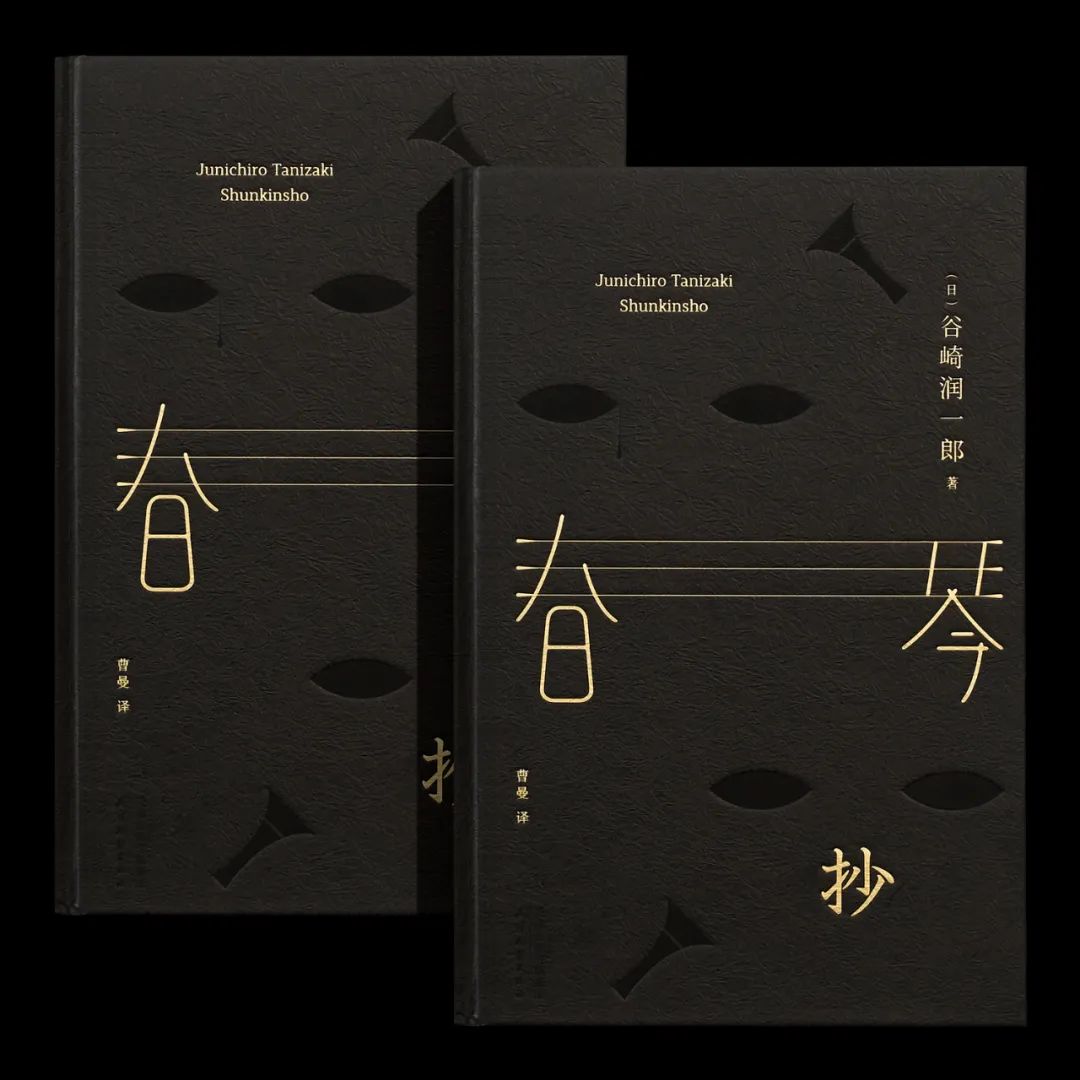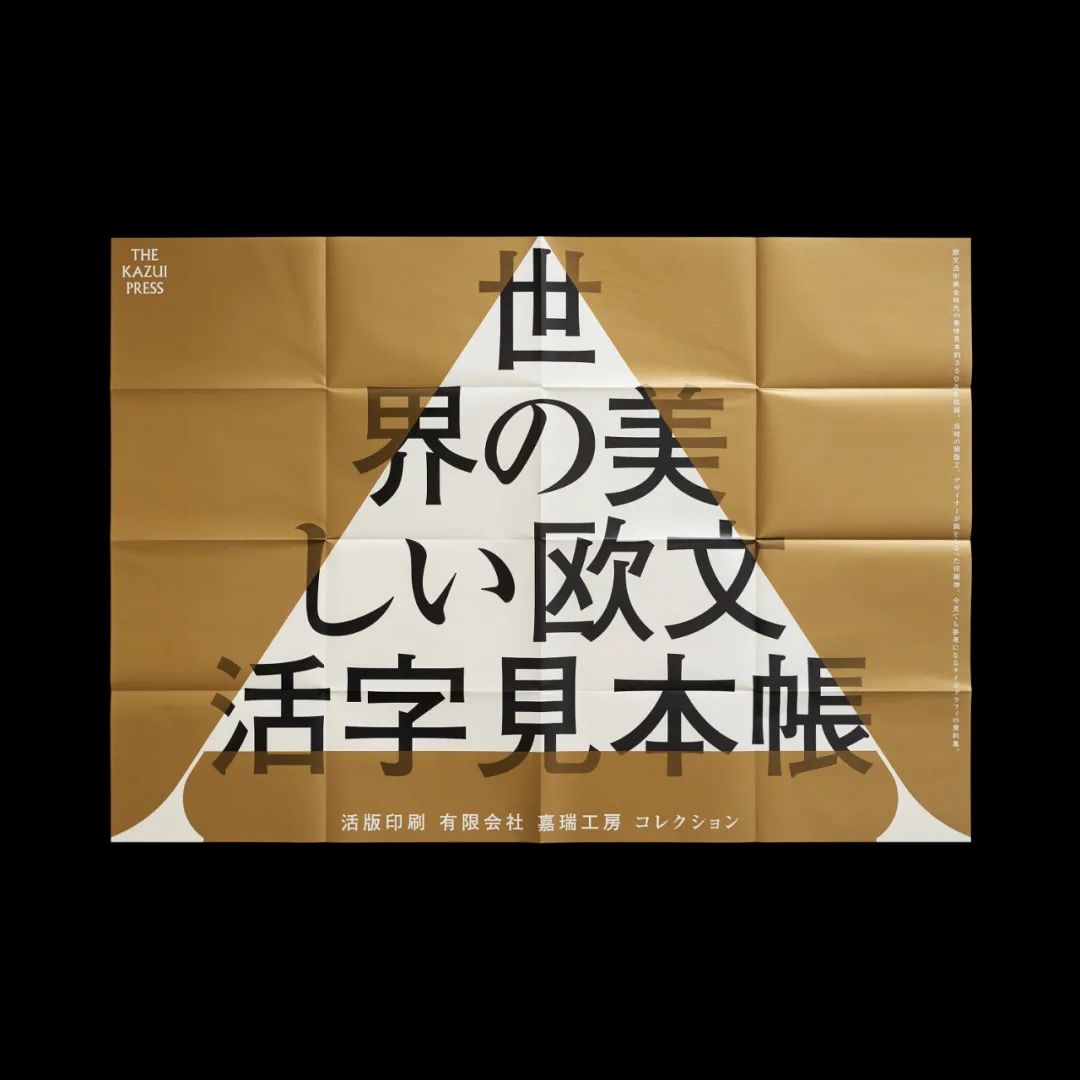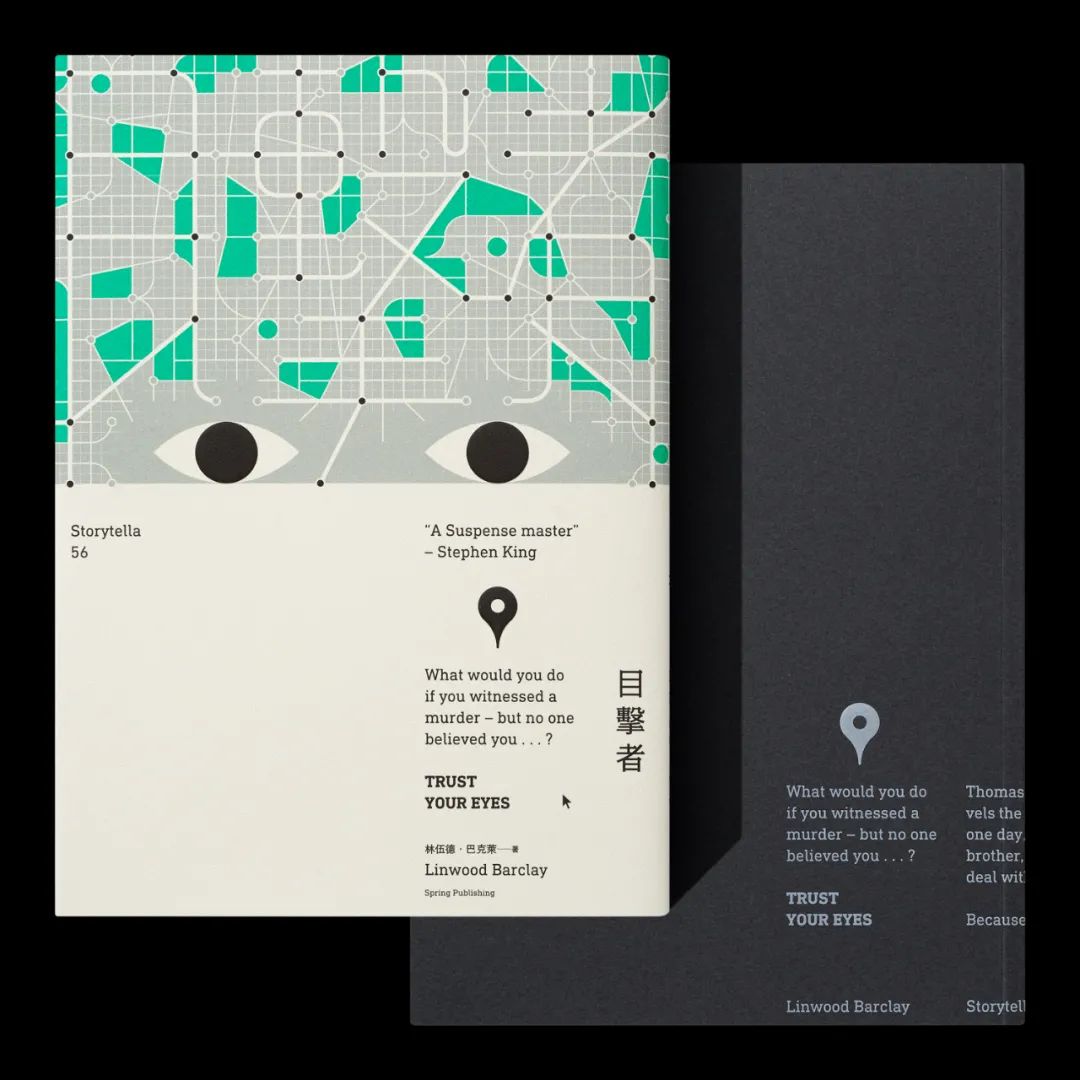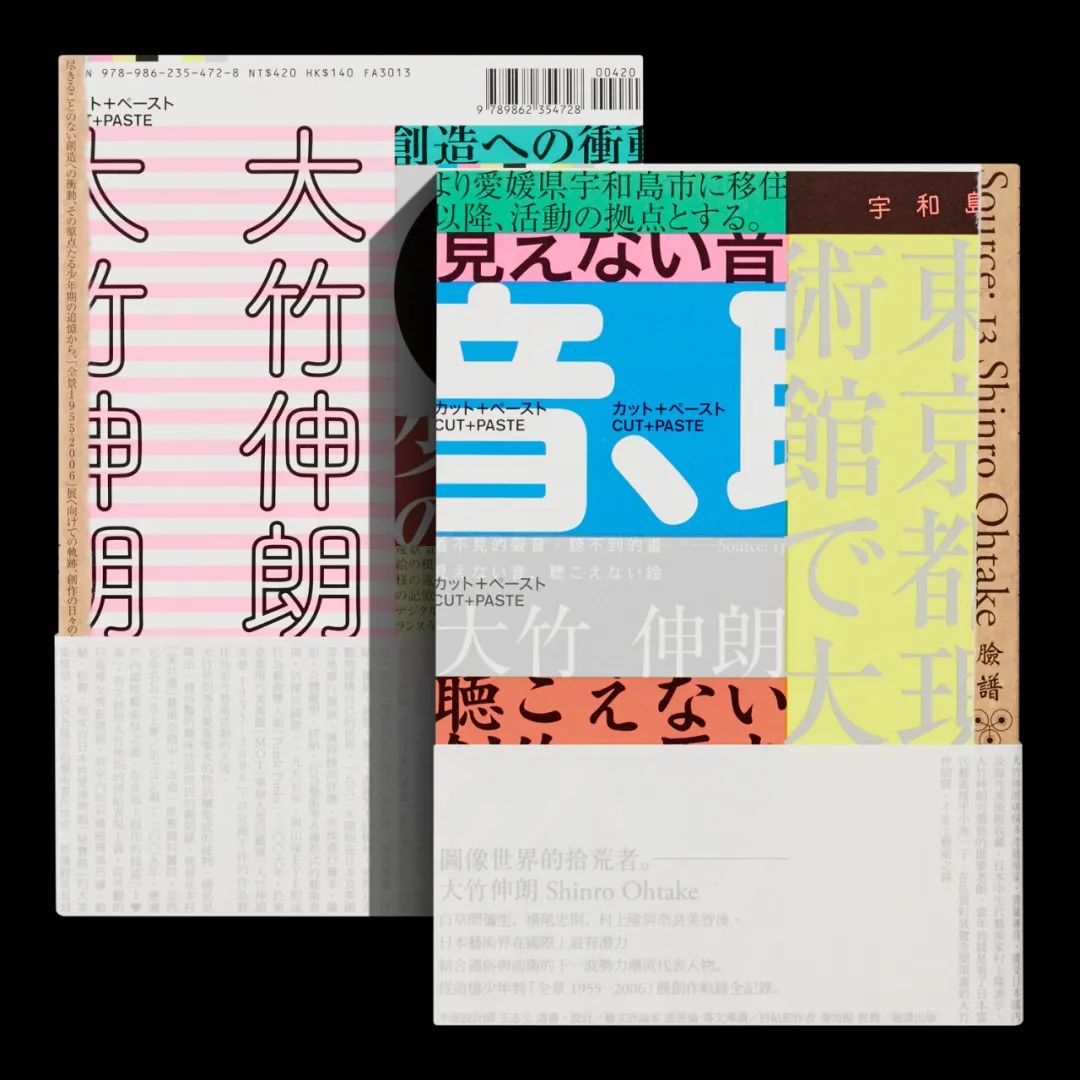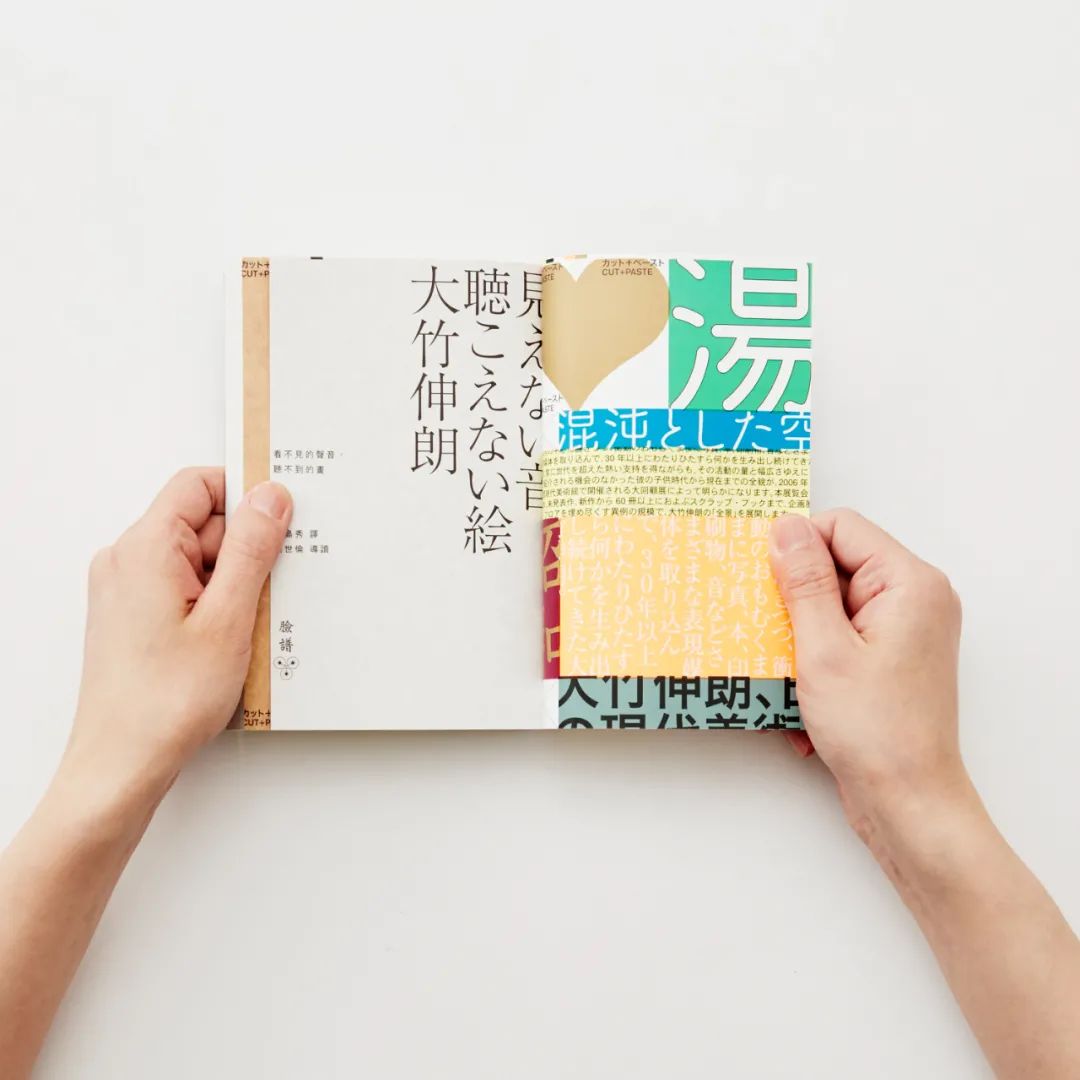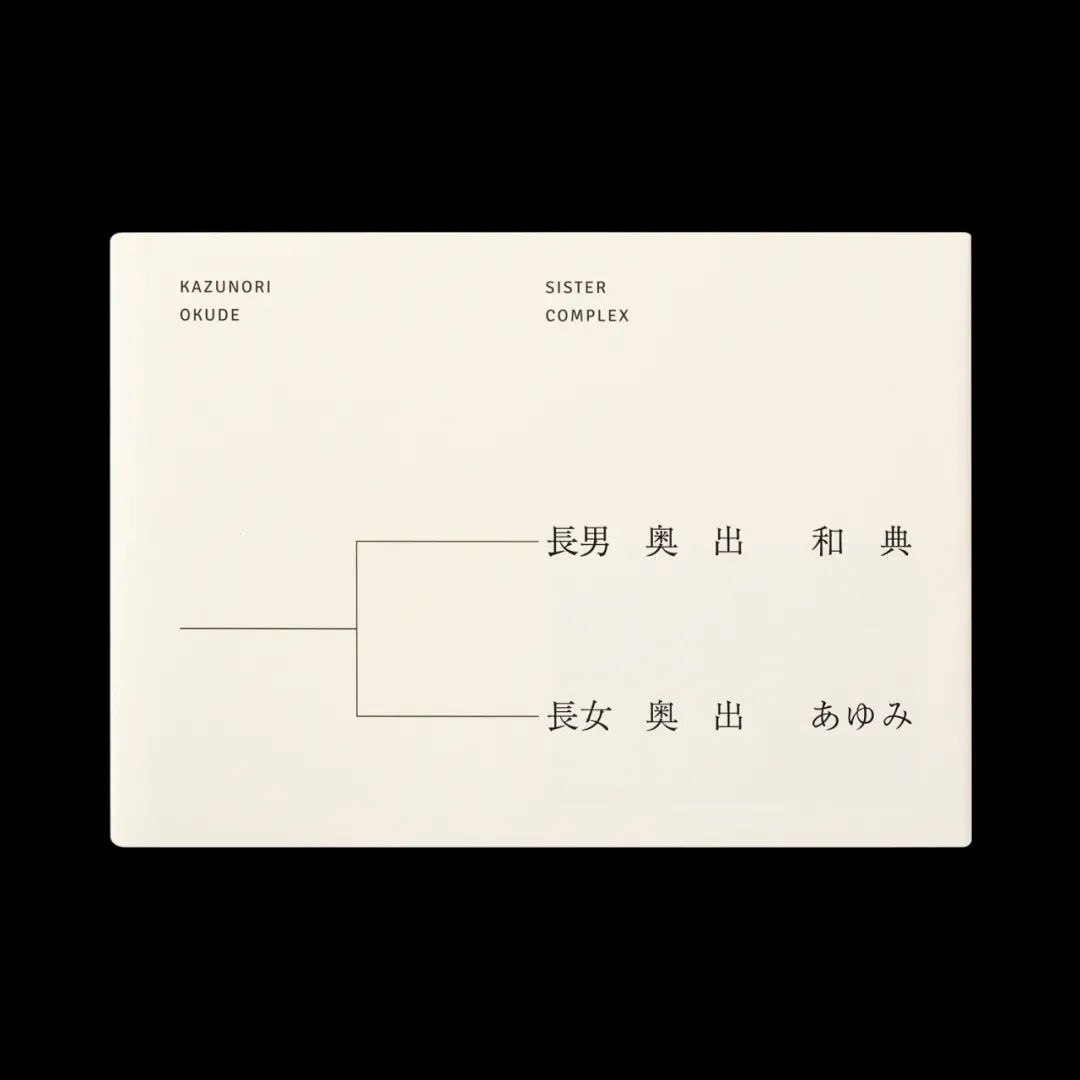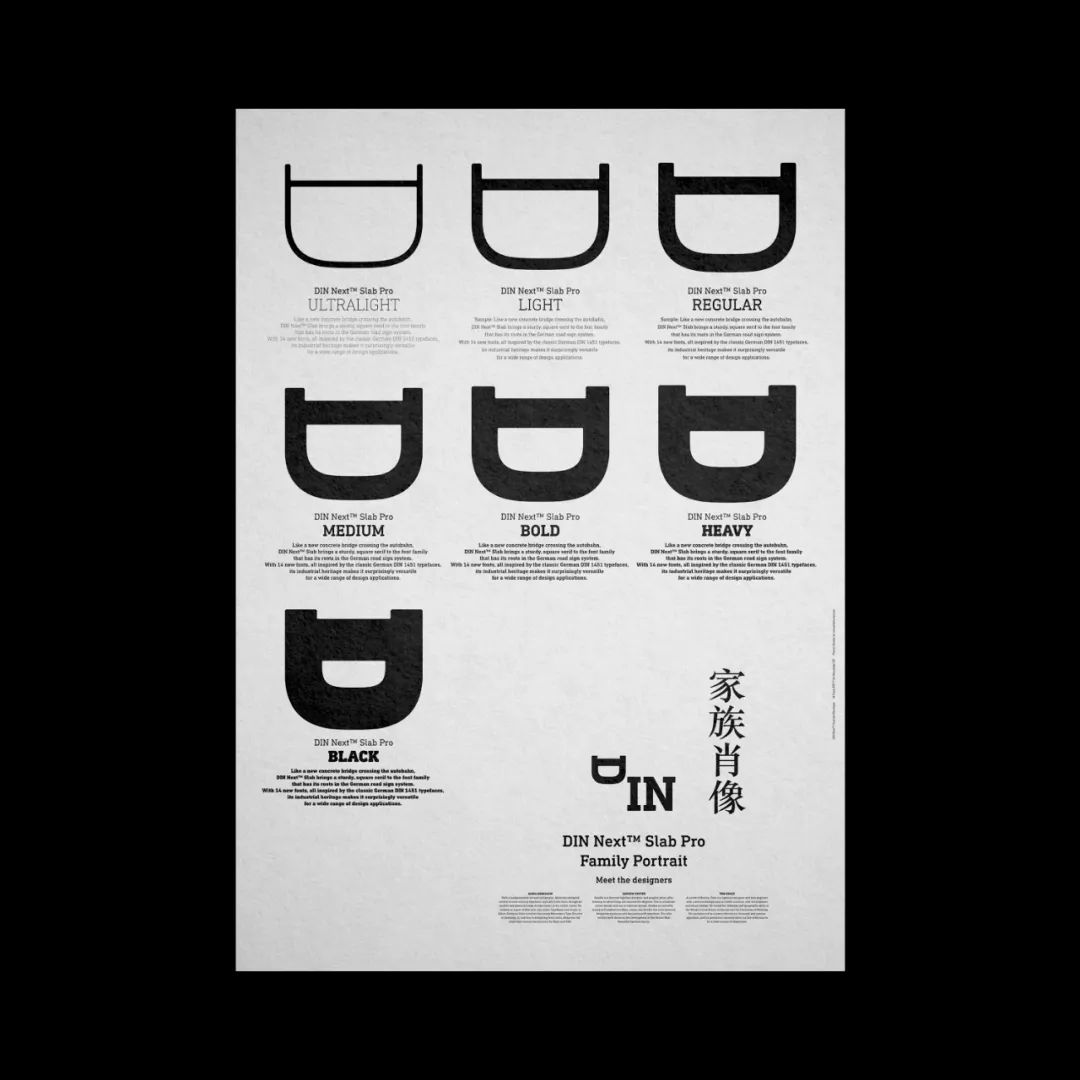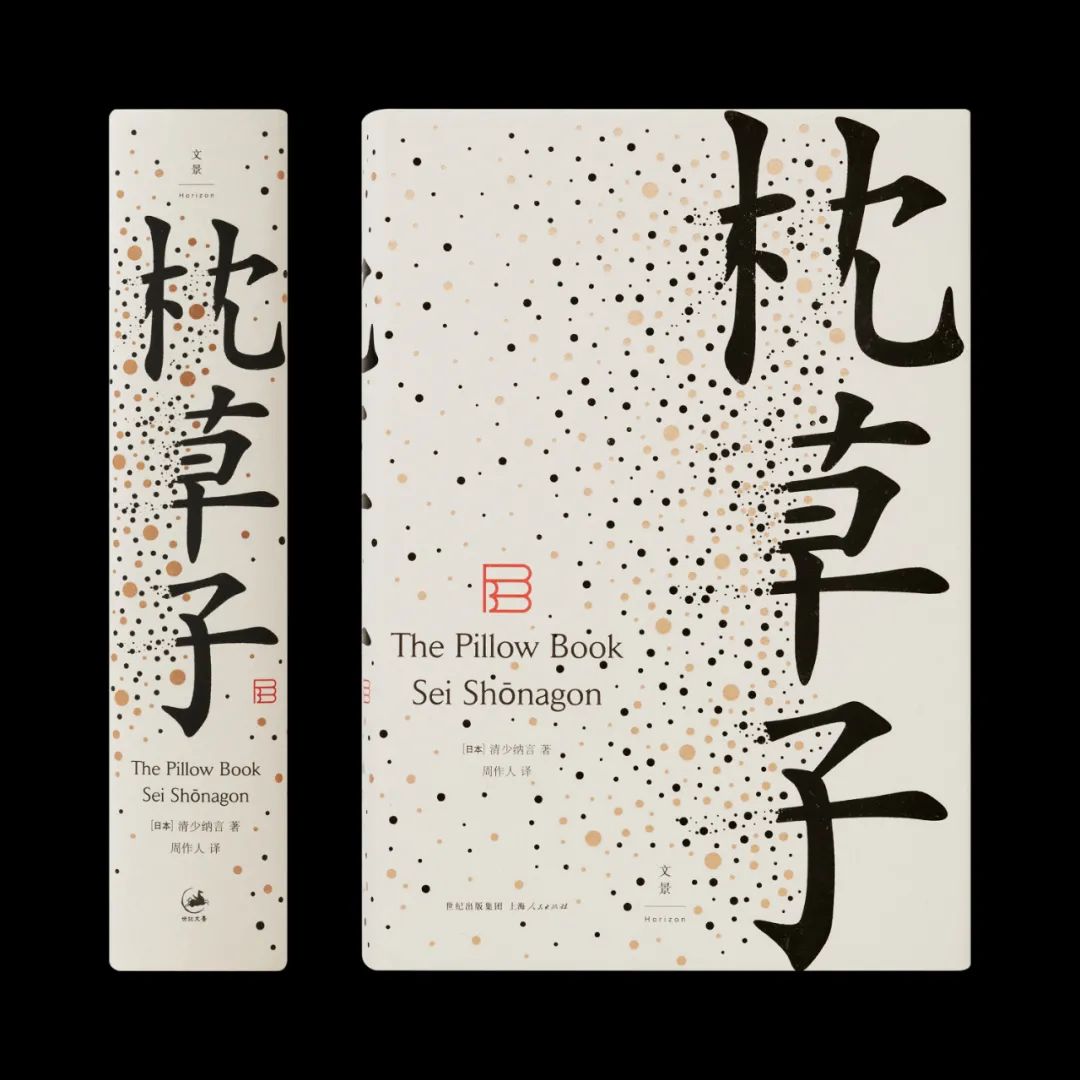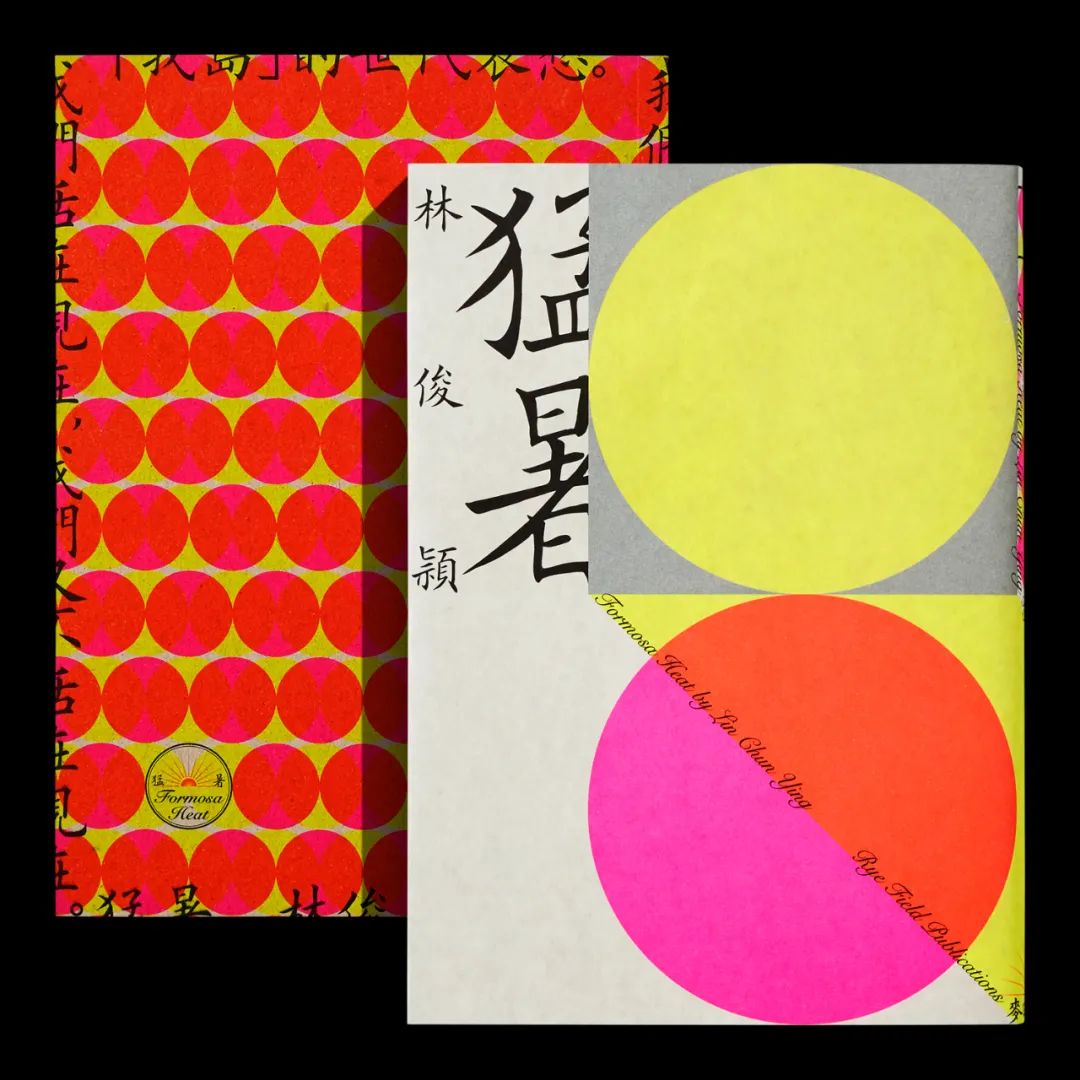
王志弘,台湾新生代设计师,2000年开始以个人工作室承接设计案,以平面设计为主;领域涵盖各类书籍、电影,及表演艺术活动等宣传制作物。
知道王志弘的人都会觉得他是一位书籍设计师,他自己是非常喜欢书籍,可却不希望被定位为书籍设计师,但是他也不介意自己设计生涯的起落点都与书籍有关。作为中国台湾新生代设计师,专注于书籍装帧设计、排版设计,将中国台湾、中国、日本和西方文化元素融合在一起,形成自己独具一格的设计风格──古典与现代相结合。
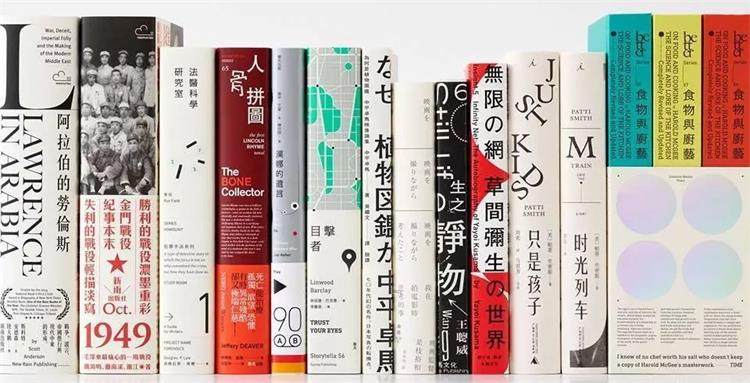
△ 王志弘部分作品展示
在设计方面,他专注于字体设计,力求将文字元素与影像元素双方相平衡,达到一种秩序与平衡的境界。王志弘通过对现代版式的解构再创作,将自己的想法与中国文字,文化相结合再传播出去让更多人认识和了解。对中国文字的发展和传承起到促进的作用。